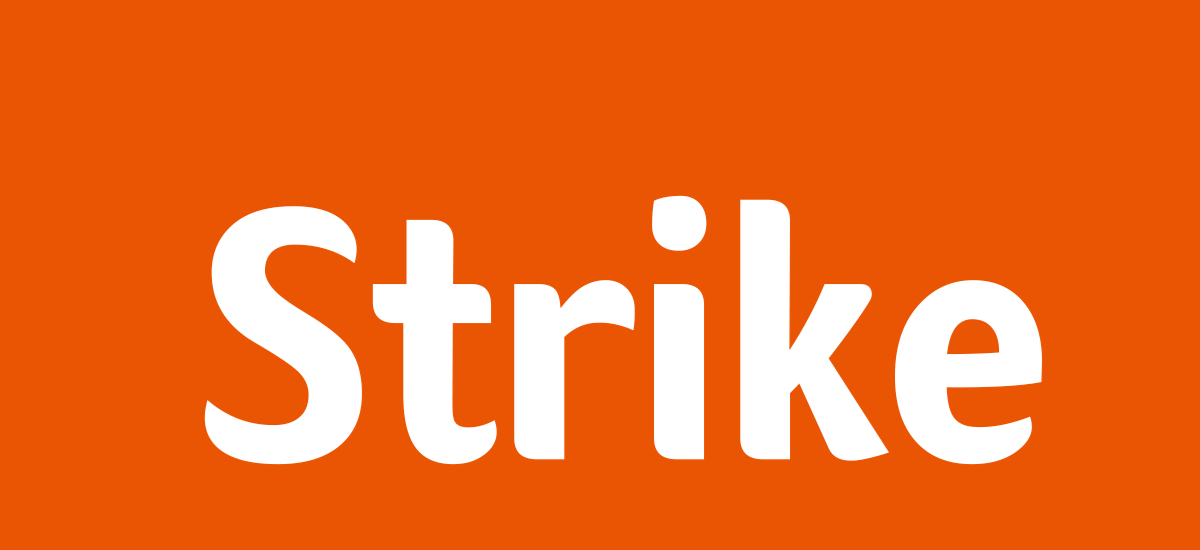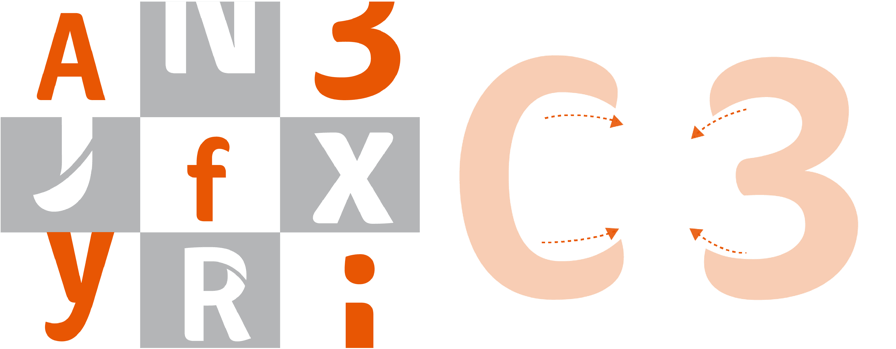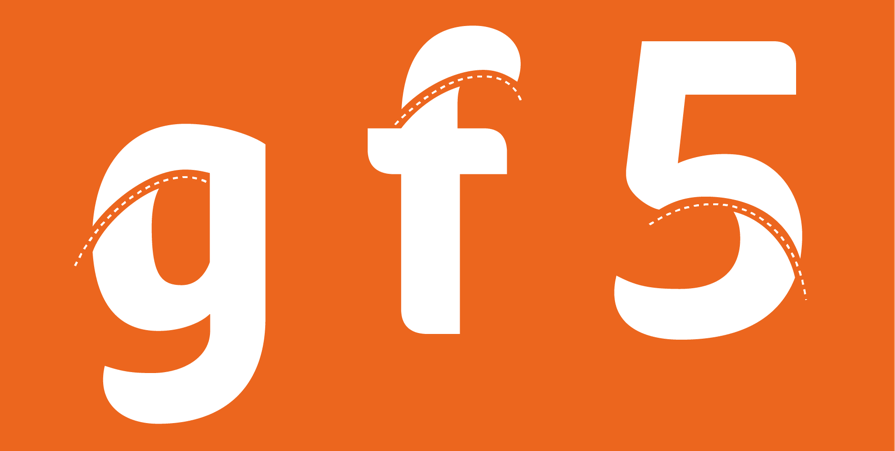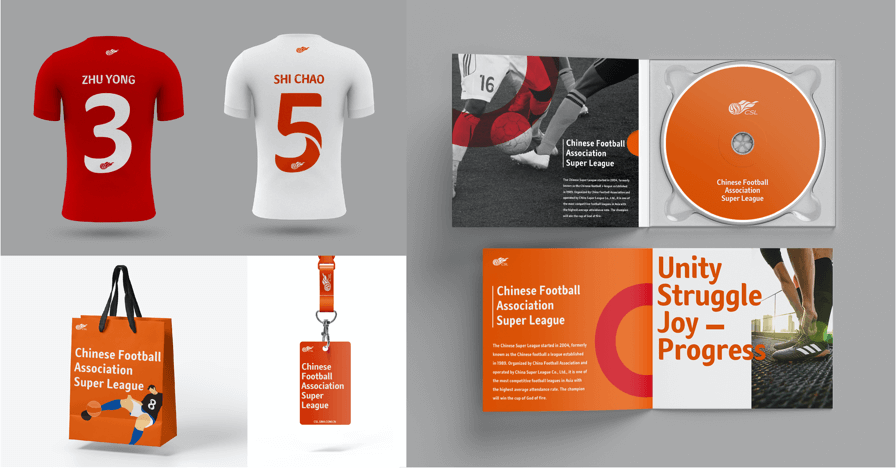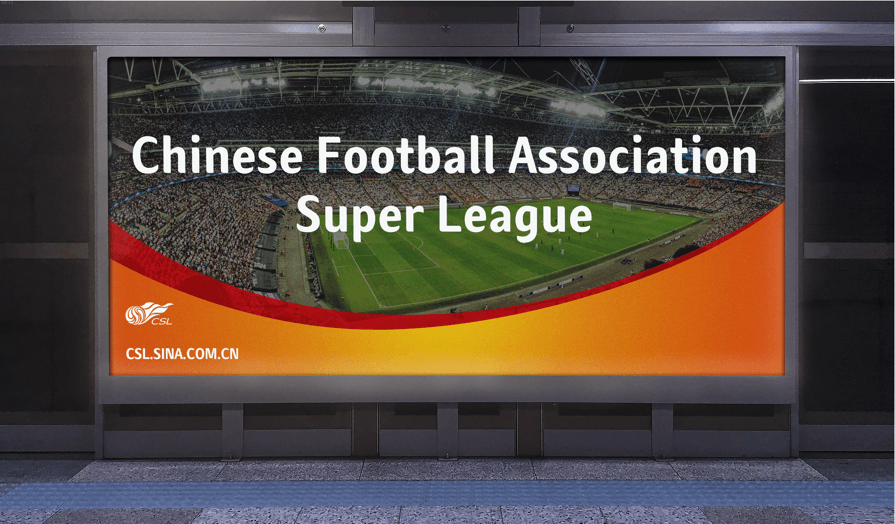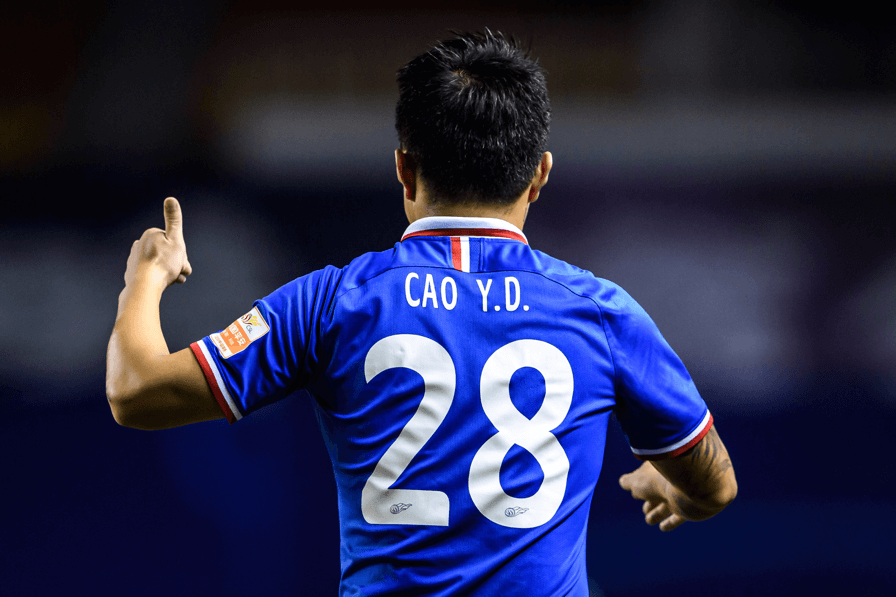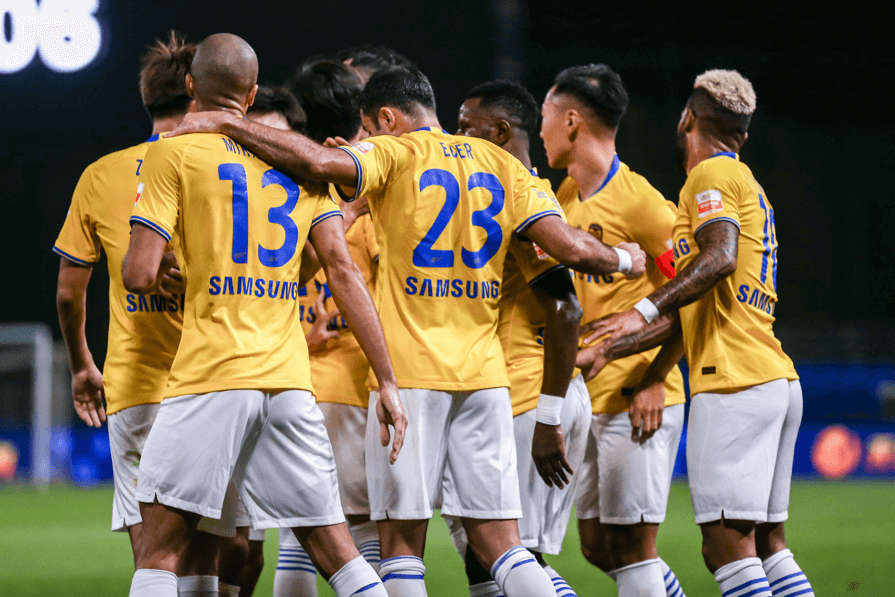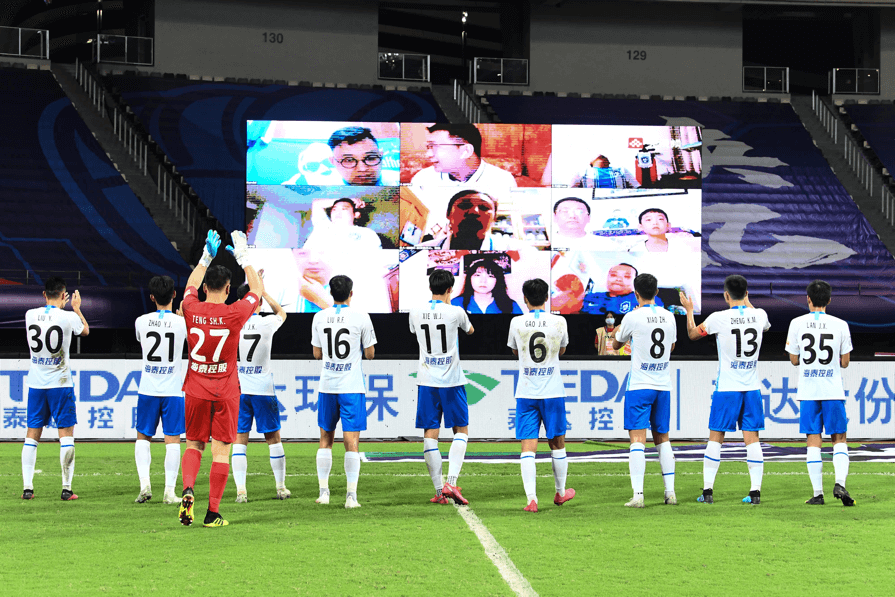
中国足球协会超级联赛
品牌定制字体
CSL Sans
中超字体设计灵感来自足球运动的特点及中超联赛logo的形态,中超联赛logo是以中国戏剧脸谱的描绘手法绘制的火球标志,该标志象征着中超联赛充满激情和活力。定制字体是定制者的形象代言人,承载着定制者的基因和气质。中超定制字体与logo遥相呼应,将活力延续,保持了中超联赛形象的统一性。独特的字体可以为赛事带来画龙点睛的效果,将特有的体育精神融入文字设计,提高识别度,建立一体化、易识别的赛事形象。
这套字体以中超口号为切入点,落脚于“团结、拼搏、欢乐、向上”等关键词,并以此为发散点进行字体设计。创作理念来自对足球运动的提炼:灵动、团结、凝聚力。球场上瞬息万变,需要踢球的人眼观六路、耳听八方,机敏果敢而不失灵动。字体线条简洁,内弧的曲线呈现环抱状,线条饱满,有张力。笔画尾部的弧度,刚柔并济,稳重亲和。整套字体通过流畅的曲线、俏皮的笔画转折展现了运动员的灵动性。
值得一提的是,笔画内部有断笔的字体笔画间形断意连,形态上相互缠绕,结构变化微妙,将足球运动的团结与互动若隐若现于字体的姿态中。同时,该字形的设计也与中超联赛的标志有相通之处,保持了中超联赛形象的统一性。
CSL Sans实际应用场景